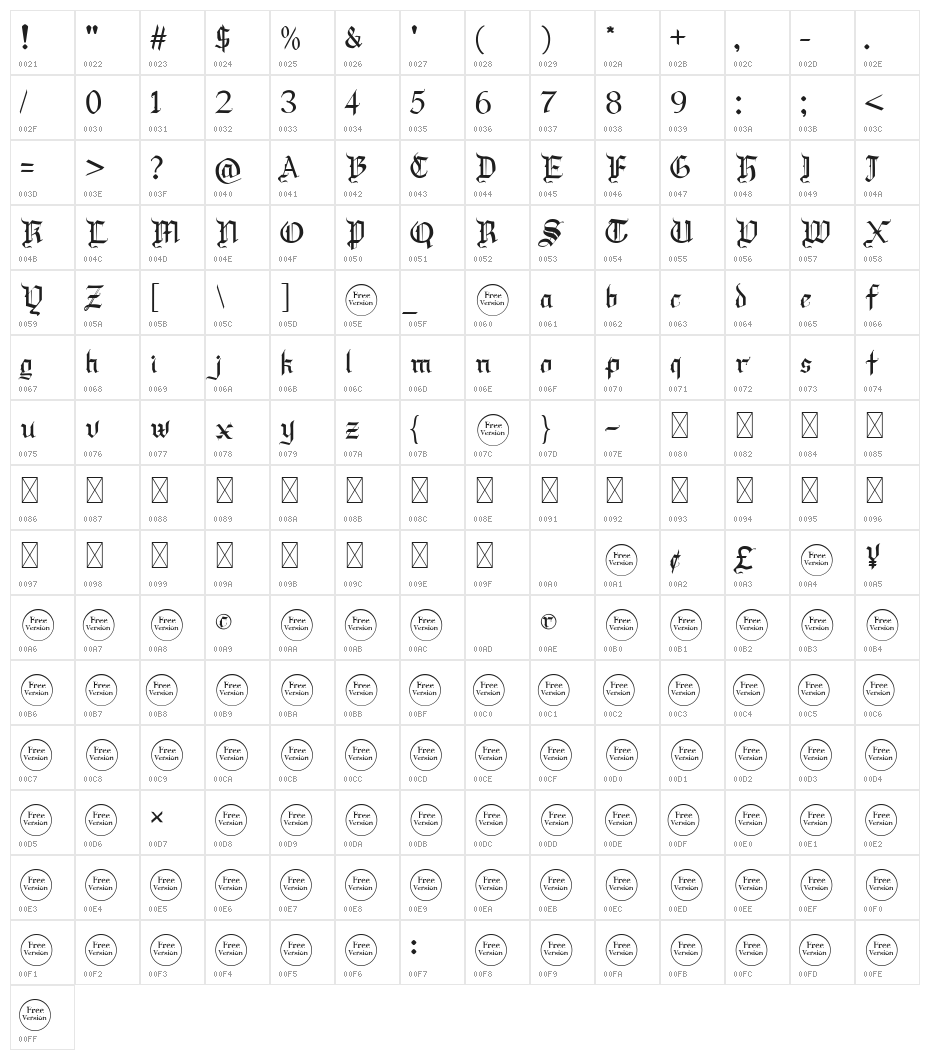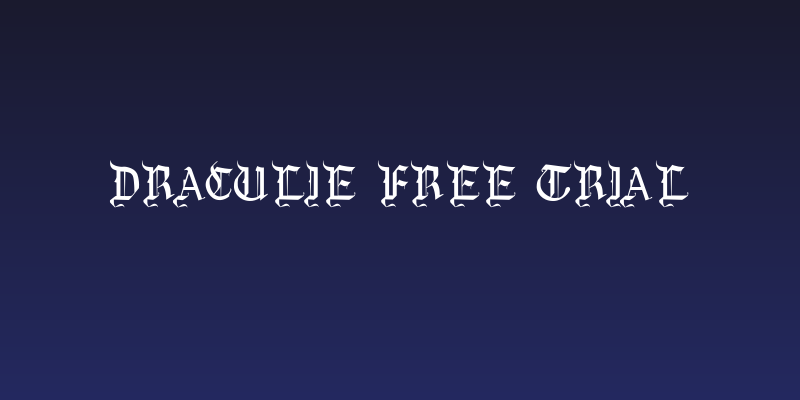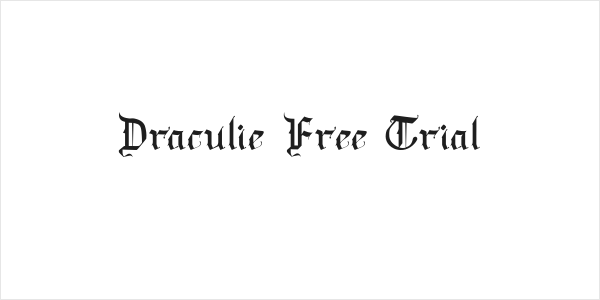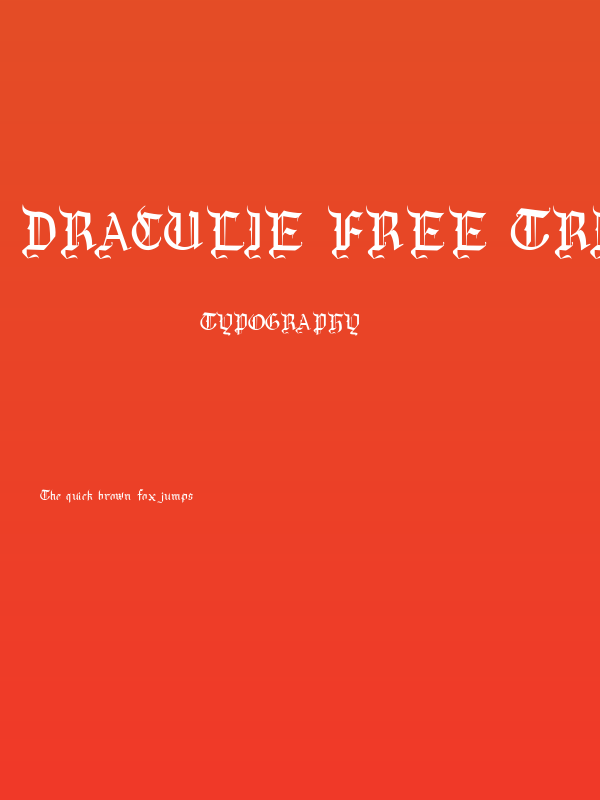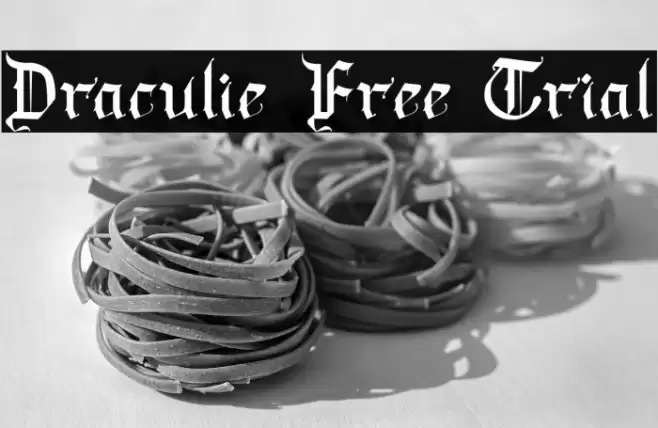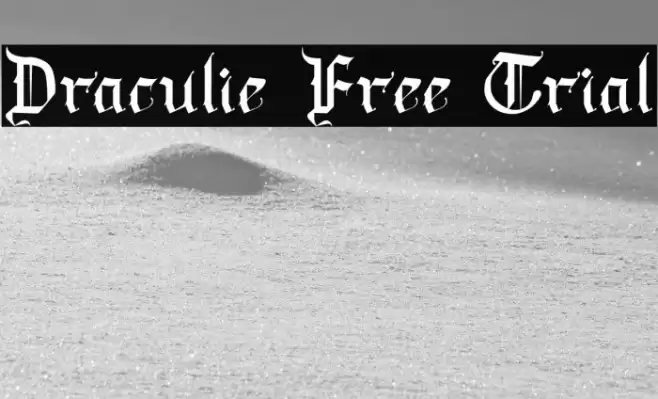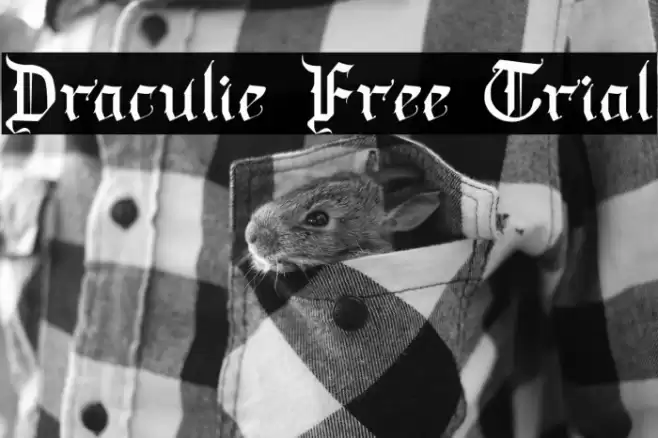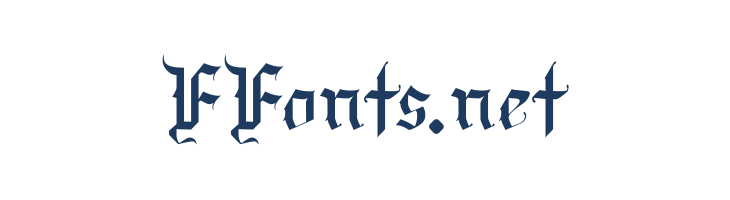
Draculie Free Trial Font
✎ Calligraphic
| Categorie | Calligraphic |
| Caso d'uso | Logos, Headlines, Decorative text |
| Progetti proposti | Ideal for historical documents, gothic-themed designs, book covers, posters, and branding that requires a dramatic and traditional touch. |